✨ 썸네일 폰트 추천 모음 ✨
클릭을 부르는 썸네일 디자인의 핵심은
강렬한 타이틀 폰트
입니다.
오늘은 썸네일에 자주 쓰이는 무료 상업용 폰트 5종을 추천해드립니다.
눈에 띄는 이미지와 조합 팁도 함께 확인해보세요!
🎯 1. 넥슨 배찌체
- 둥글고 굵은 고딕 계열
- 제목 강조용으로 활용도 높음
- 배경색과 명도 대비 시 더 강력
🎯 2. 한겨레결체
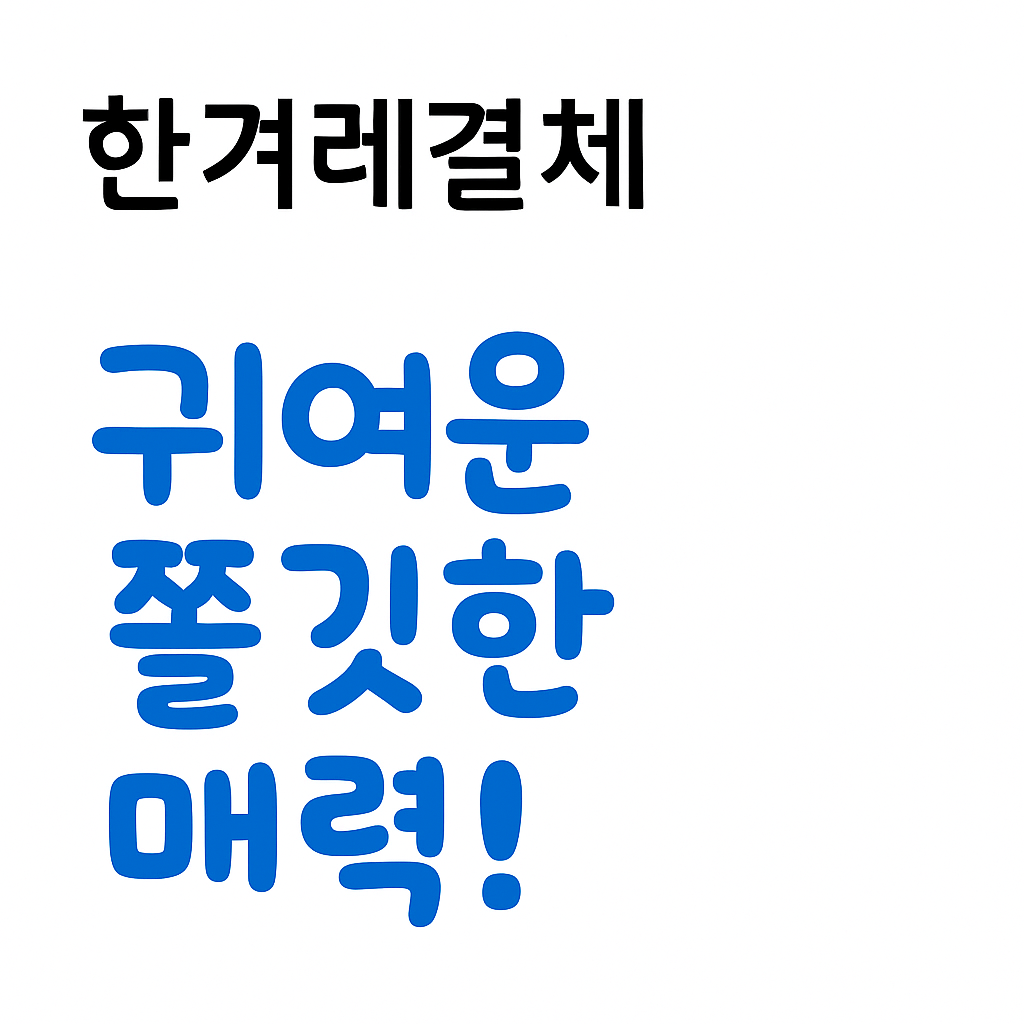
- 붓글씨 느낌의 강조 텍스트용
- 감성·감정 표현 썸네일에 적합
🎯 3. 티몬체
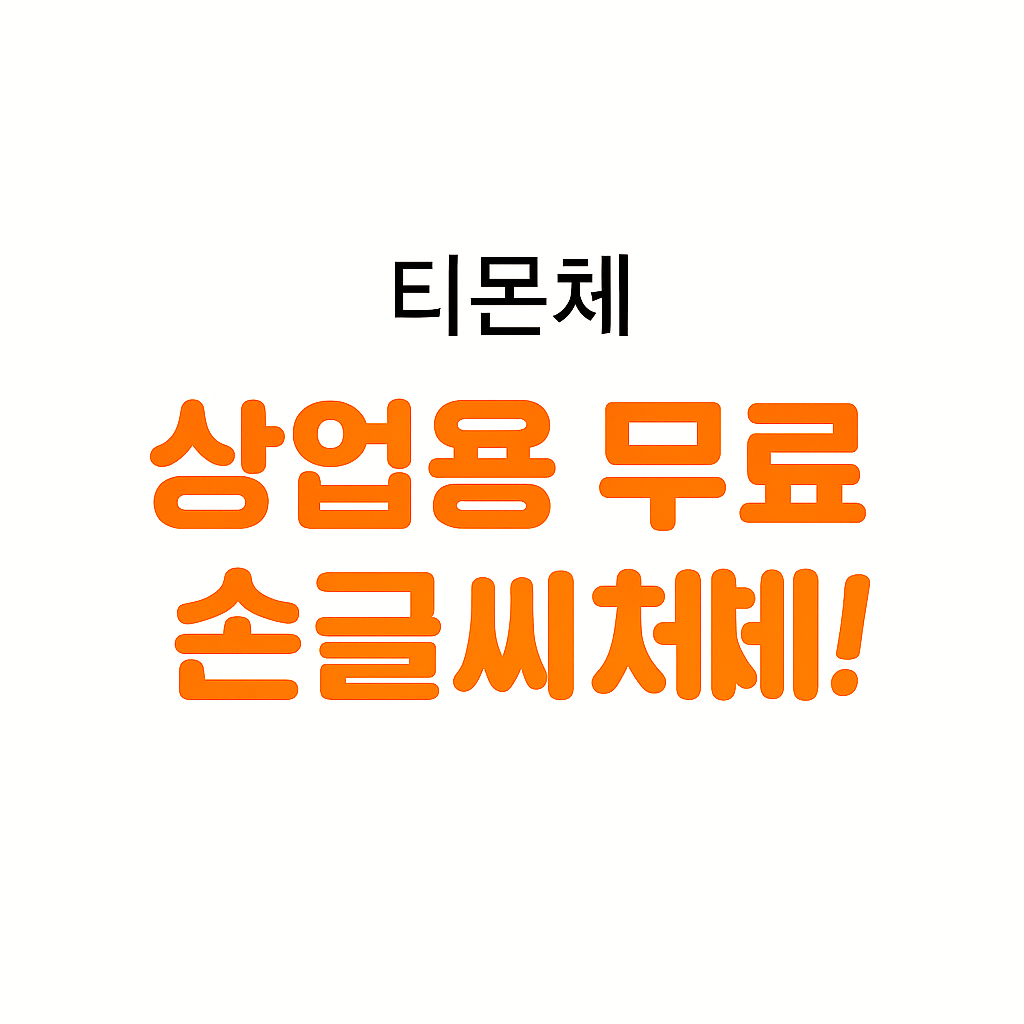
- 굵고 짧은 인상으로 가독성 높음
- 숏폼·강의 썸네일에 많이 사용
🎯 4. 나눔스퀘어라운드
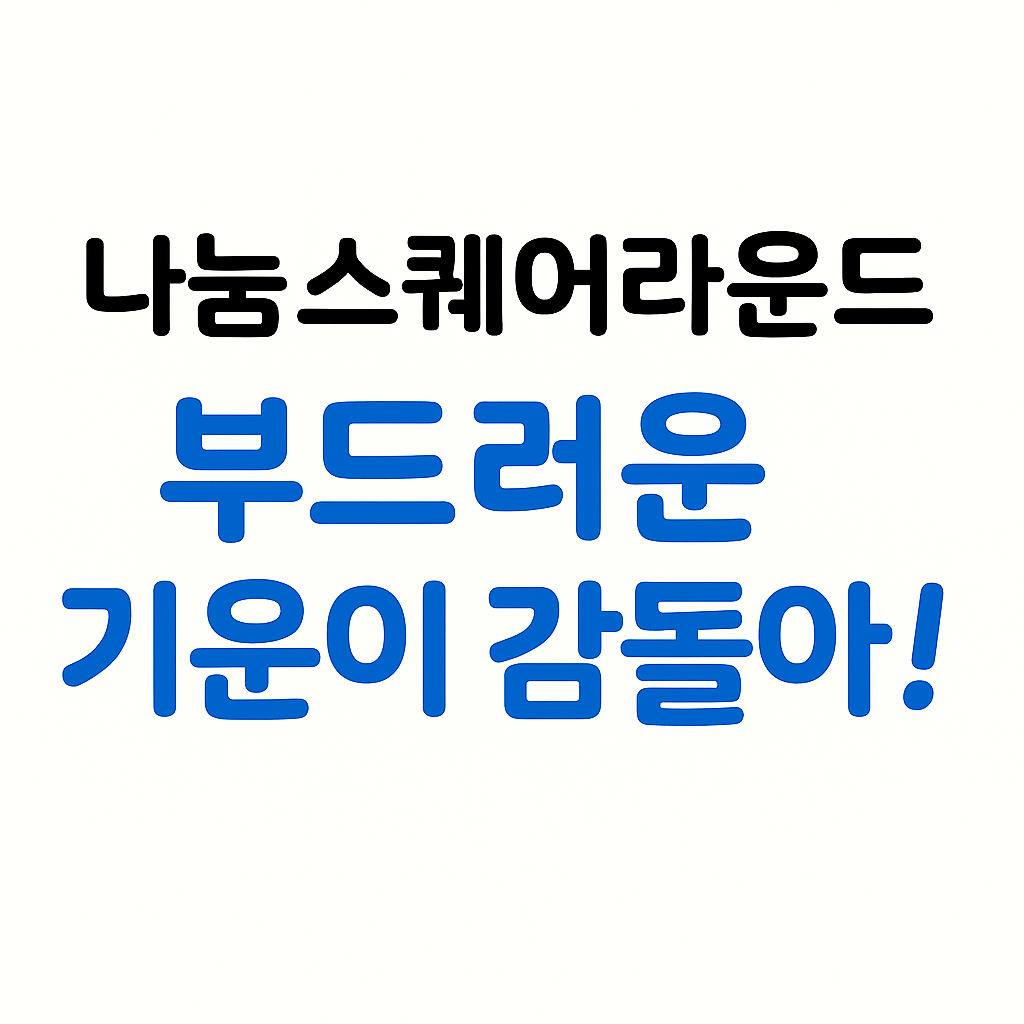
- 안정감 있는 굵은 제목용 글꼴
- 정보성 콘텐츠와 잘 어울림
🎯 5. 배민도현체
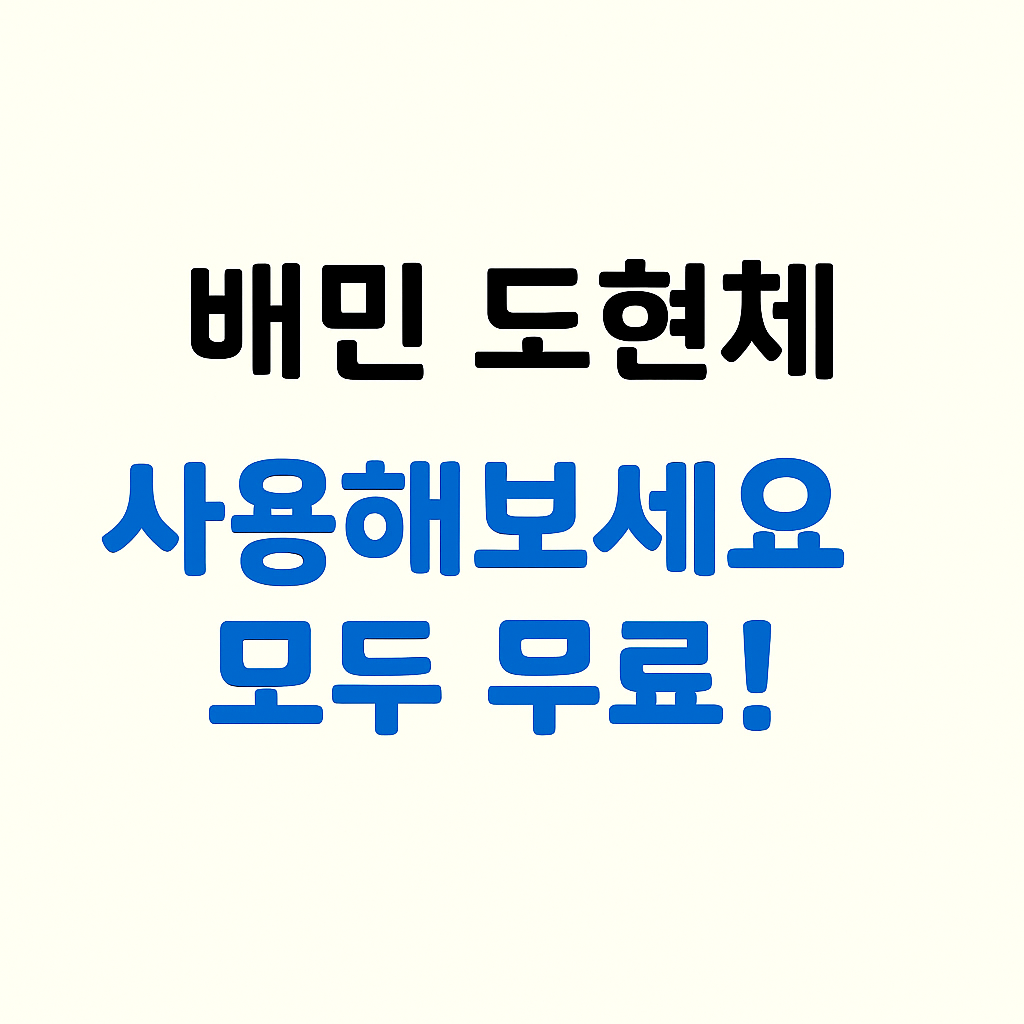
- 묵직한 손글씨 느낌
- 제품 리뷰, 감성 썸네일에 추천